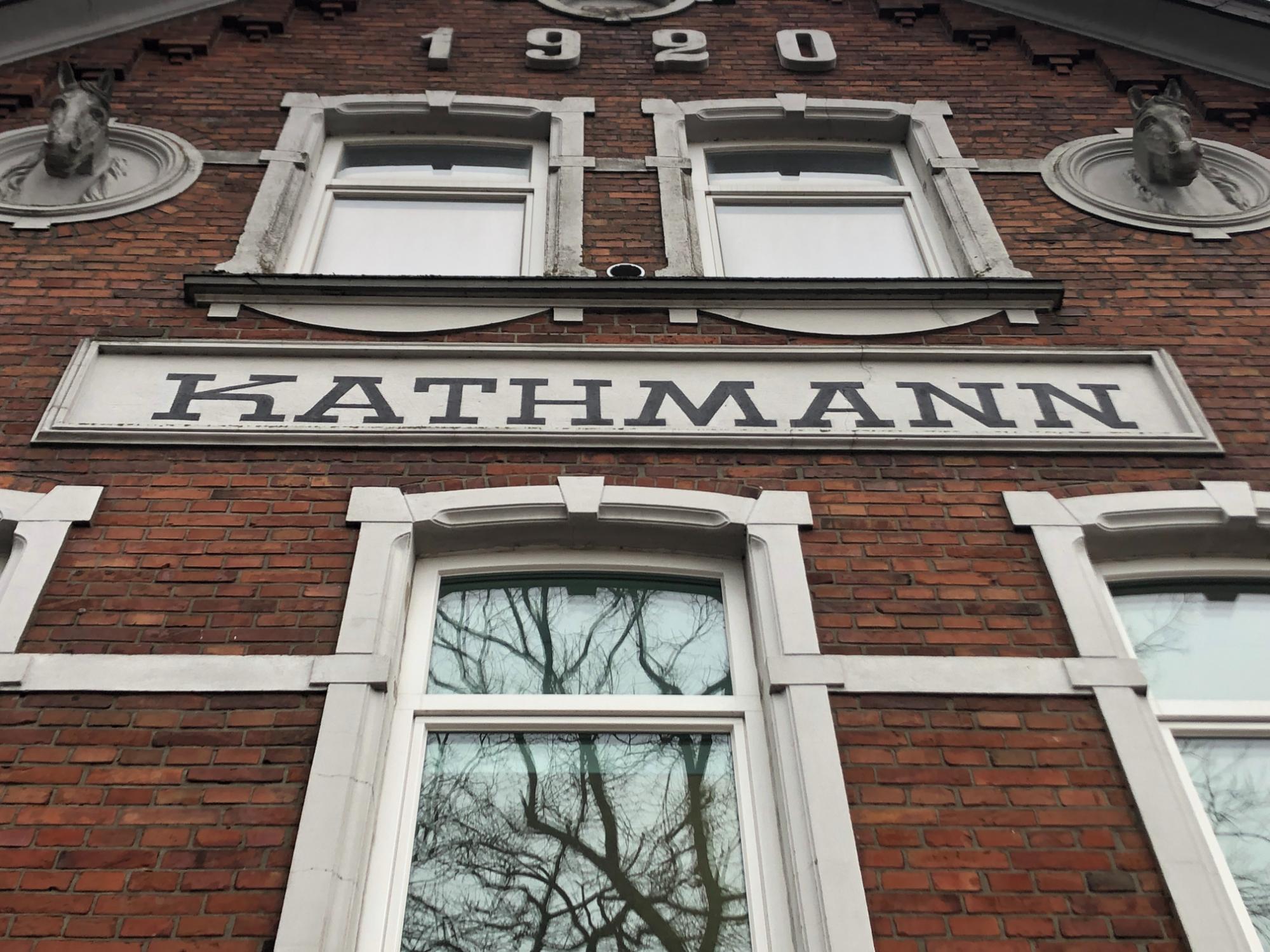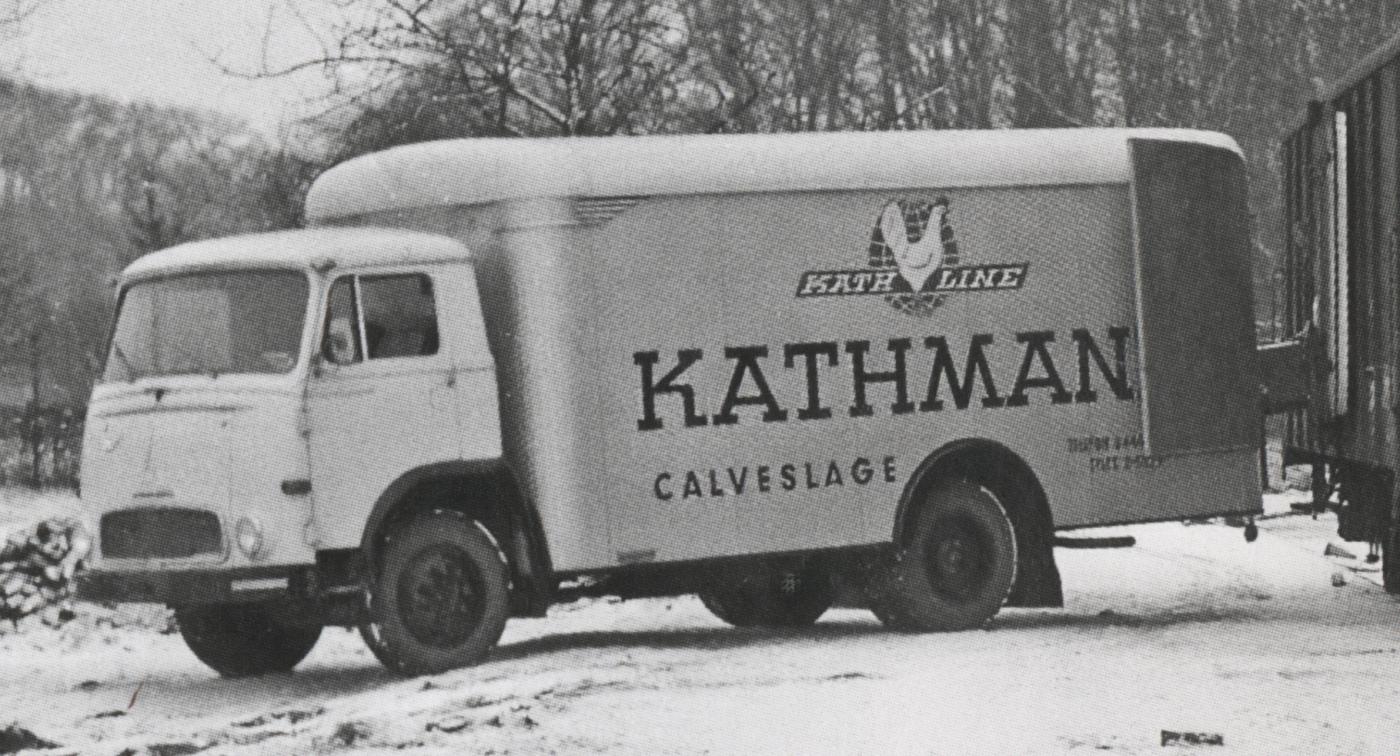
Fassadenschrift gesucht (Kathmann)
Nach längerer Recherche in Musterbüchern (u.a. „Handbuch der Schriftarten“ von 1926) und vergeblichen Onlinesuchen, wende ich mich nun an euch. Vielleicht könnt ihr mir einen Tipp zur verwendeten Schrift geben. Das Gebäude wurde 1920 errichtet und diente einem Geflügelausrüster als Stammhaus.
Die perspektivische Verzeichnung habe ich zur besseren Beurteilbarkeit entfernt. Möglich ist natürlich auch, dass es sich um eine Schablonenschrift handelt, die vom damaligen Malermeister „interpretiert“ wurde.
Ich habe noch ein Foto von einer Fahrzeugbeschriftung aus den 1960er Jahren gefunden – inkl. „Kursivschnitt“ bei „KATH LINE“. Damals hatte man vermutlich mit einer Werbeagentur (wahrscheinlich aus Bremen) zusammengearbeitet. Mehr Details habe ich aber derzeit nicht.
Eine Font-Alternative dazu wäre zum Beispiel diese:
Könnte man als Basis nutzen und das K entsprechend abwandeln.
Ein Schriftmuster, welches in die richtige Richtung geht (aber nicht passt): https://www.myfonts.com/products/urw-glamour-volume-package-328822
Das verstehe ich nicht. Ist doch etwas völlig anderes. 🤷🏼‍♂️
Da hast du natürlich recht – ich wollte damit nur zeigen, dass es eine Schriftart mit so einem „Spezial-K“ gibt.